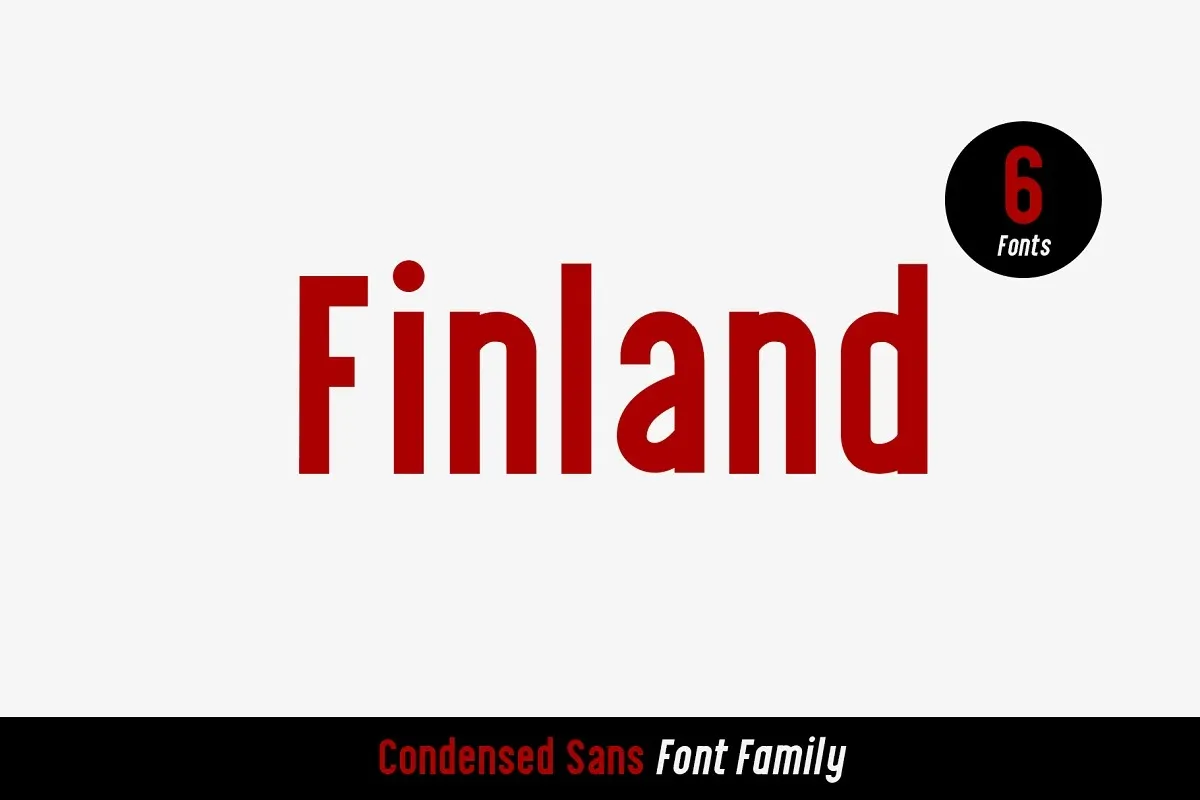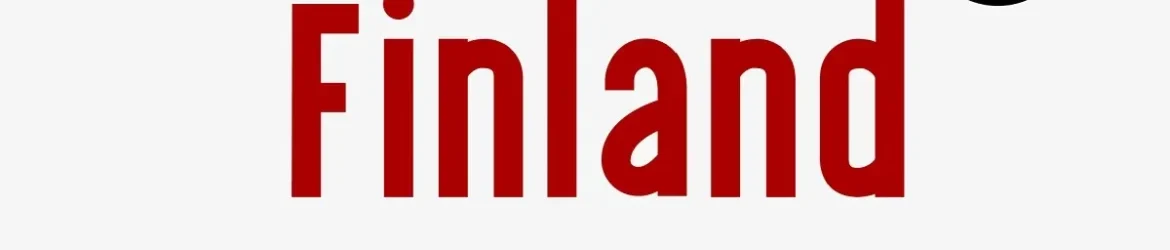
A Finland Font é uma elegante tipografia sans-serif desenvolvida pela Craft Supply Co., inspirada nas antigas publicações de tipos europeias, particularmente na estandardização do tipo finlandês. Inspirado nos valores fortes dos pioneiros da indústria gráfica e atualizado para atender às demandas atuais do mundo tecnológico, a Finland Font se destina à alta profissionalidade no uso dos arquivos digitais. Seu estilo limpo e ágil combina perfeitamente com uma ampla gama de formatos de mídia digital, tornando-a uma escolha confiável para qualquer projeto que exige um toque contemporâneo e de alto padrão.